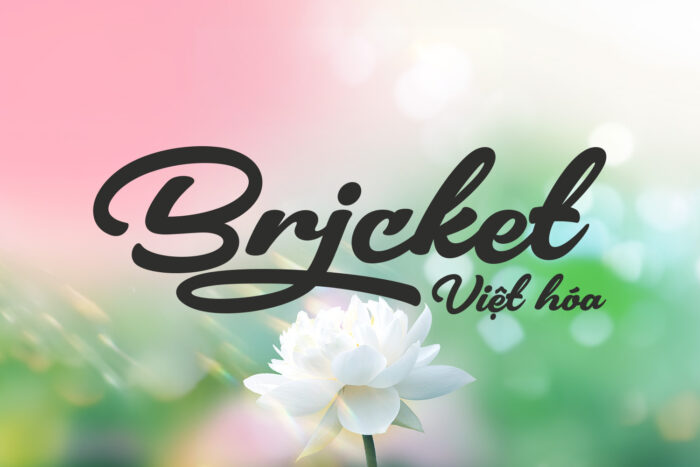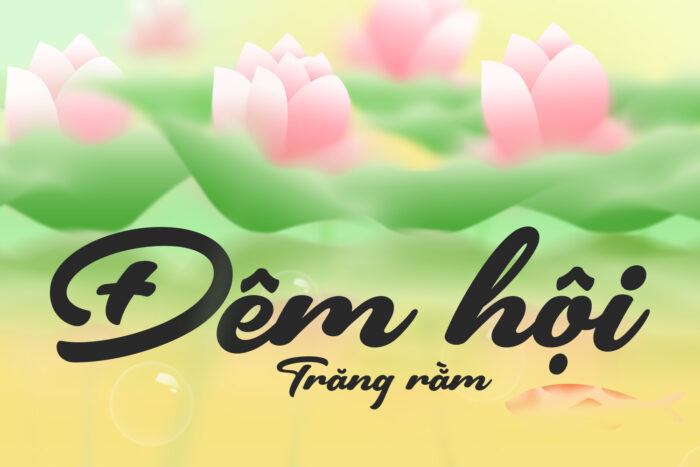
DVN Bricket Việt Hóa – Font Chữ Thư Pháp Hiện Đại và Cuốn Hút
Font chữ “Bricket” là một kiểu chữ hiện đại thuộc loại calligraphy, mang phong cách thư pháp với thiết kế mềm mại và uyển chuyển. Các đường nét của “Bricket” được uốn lượn mượt mà, tạo nên sự tinh tế và thanh lịch trong từng chữ cái. Đặc trưng nổi bật của font chữ này là sự liên kết liền mạch giữa các chữ, mang lại cảm giác liên tục và liền lạc.
Với độ dày của nét chữ không đều, “Bricket” tạo điểm nhấn độc đáo, giúp từng chữ cái trở nên sống động và thu hút. Font chữ này rất thích hợp để sử dụng trong các thiết kế liên quan đến thời trang, làm đẹp, hoặc các sản phẩm cao cấp. Nó cũng phù hợp cho các tiêu đề, logo, và những ấn phẩm cần sự nổi bật và phong cách riêng biệt. “Bricket” sẽ là lựa chọn lý tưởng cho những ai muốn tạo nên một dấu ấn đặc biệt và đẳng cấp trong các thiết kế của mình.